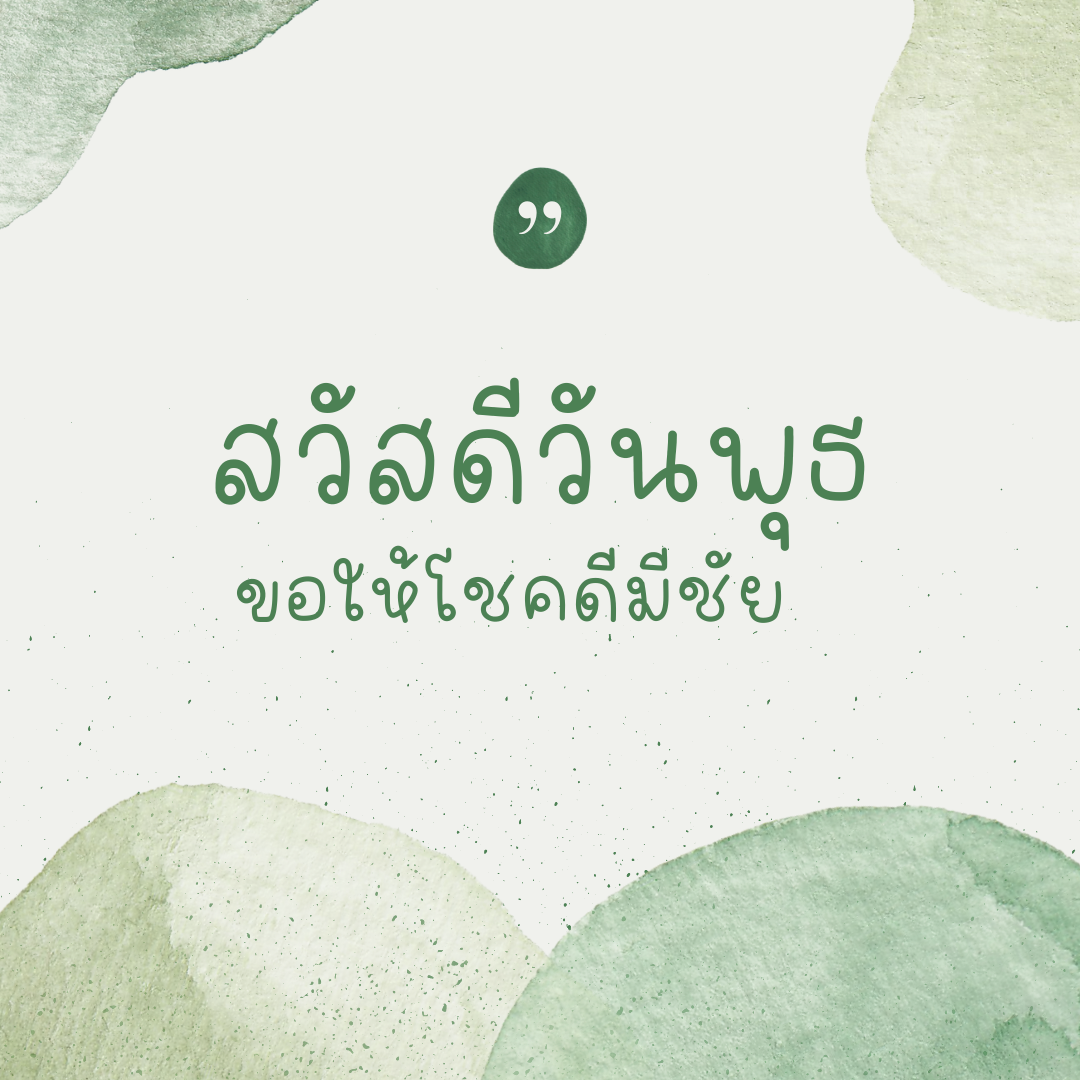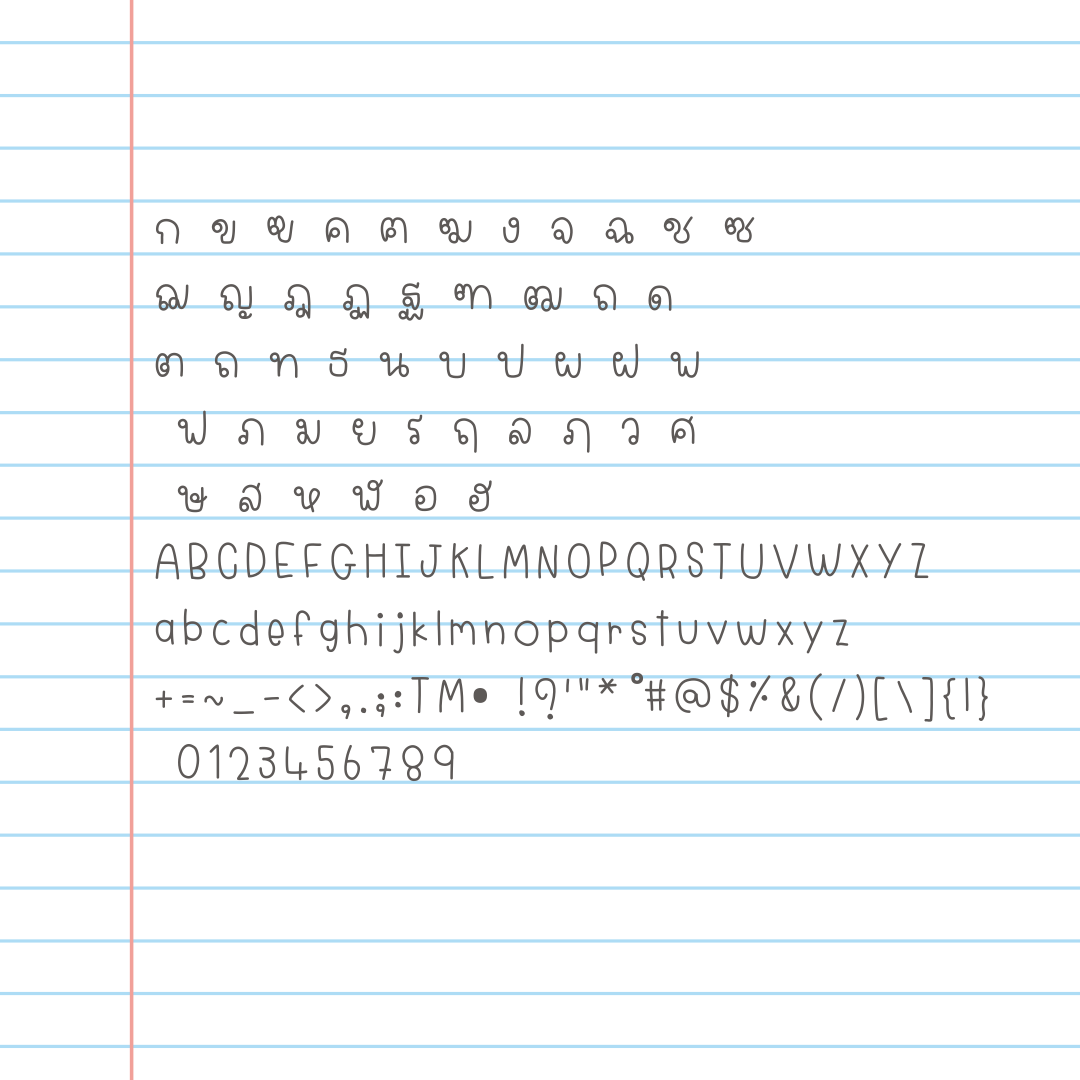
จอนนี่ (Johnny)
ฟอนต์ จอนนี่(Johnny) ฟอนต์ที่มีเอกลักษณ์ ใช้ทำงานสไตล์น่ารักๆ จดโน้ต หรือจะทำแฟลชการ์ดก็ดูดี แจกฟรีไปเลยเวอร์ชันทดลอง : แบบปกติ 1 น้ำหนัก ใช้ได้เฉพาะแบบส่วนตัว เช่น ใช้ในการศึกษา ใช้จด ใช้ตกแต่งสมุดโน้ตตัวเอง